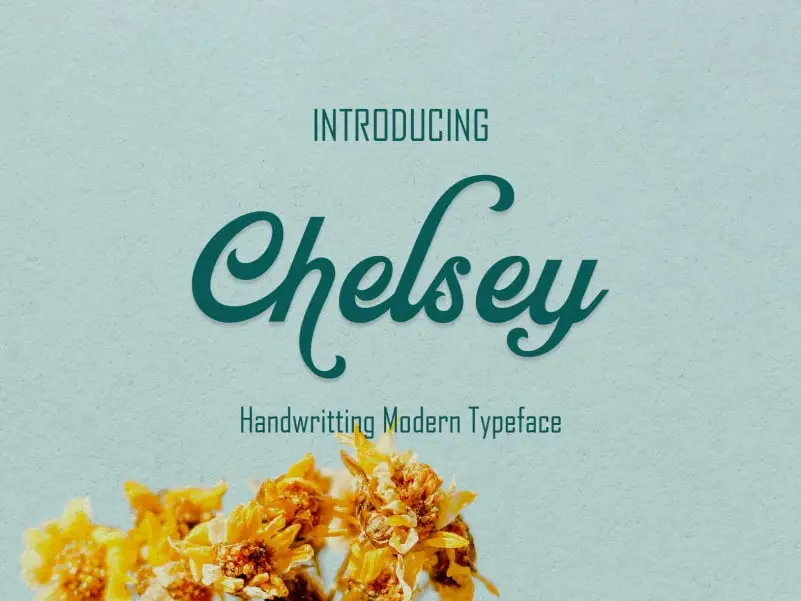
Chelsey Script Font – Download Grátis
A Chelsey Script Font é uma elegante tipografia script que combina harmoniosamente com as escritas manuscritas decorativas para enriquecer projetos de design. Perfeita tanto para trabalhos profissionais quanto para logotipos, marcações e letra de citações, essa fonte é perfeitamente adequada para capas de livros, menus de restaurantes, embalagens de produtos alimentícios, etiquetas de bordados, rótulos de chá orgânico, logomarcas de equipes esportivas ou qualquer outro campo similar. Com alternativas contextuais e ligaturas padrão que mantêm as conexões fluidas, essa fonte é perfeita para quem deseja agregar um toque sofisticado a seus projetos. Seu designer, Aldi Wangsadipa, equipou o Chelsey Script Font com todas essas características avançadas para garantir um resultado profissional e envolvente em qualquer projeto de design que você esteja criando.